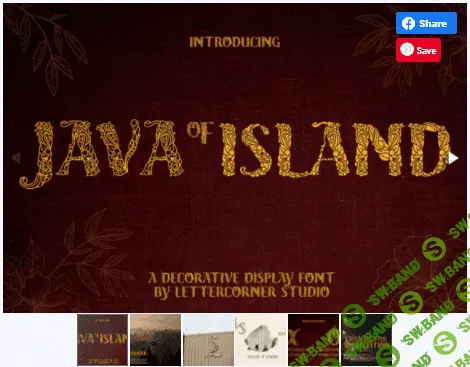
Название: Java Island Font (2021)
Java Island - красивый декоративный шрифт с высокой детализацией. Этот шрифт, искусно созданный для того, чтобы ваше творение выглядело необычно, отлично подойдет для самых разных идей.